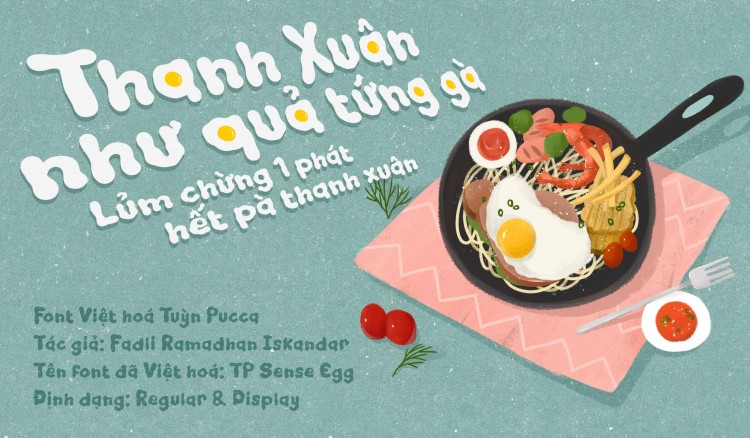
Font việt hoá TP Sense egg (2 font)
Trong thế giới thiết kế đồ họa hiện nay, việc lựa chọn một bộ Font Miễn Phí chất lượng đóng vai trò cực kỳ quan trọng để tạo nên linh hồn cho tác phẩm. Một trong những bộ phông đang thu hút sự chú ý của cộng đồng sáng tạo chính là Font việt hoá TP Sense egg (2 font). Đây là một bộ font sở hữu phong cách hiện đại, thanh lịch nhưng không kém phần độc đáo. Với sự hỗ trợ đầy đủ các ký tự tiếng Việt, bộ font này giúp các bạn học sinh và thầy cô giáo dễ dàng thiết kế các slide bài giảng, báo tường hay các dự án truyền thông học đường một cách chuyên nghiệp và đồng bộ nhất.
Khám phá đặc điểm nổi bật của Font việt hoá TP Sense egg (2 font)
Phong cách thiết kế bo tròn tinh tế
Bộ Font việt hoá TP Sense egg (2 font) gây ấn tượng mạnh nhờ cấu trúc các chữ cái được bo góc mềm mại, tạo cảm giác thân thiện và gần gũi. Với hai biến thể trong cùng một bộ, người dùng có thể linh hoạt thay đổi giữa độ dày và mỏng để nhấn mạnh các thông điệp quan trọng. Các đường nét được xử lý mượt mà, đảm bảo khả năng hiển thị tốt trên cả màn hình kỹ thuật số lẫn bản in giấy.
Tính ứng dụng cao trong